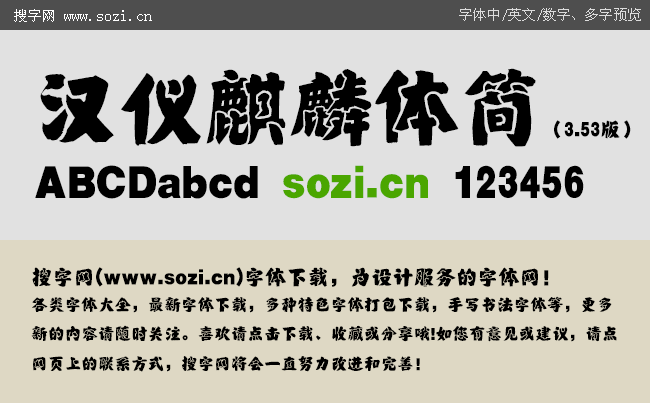
漢儀麒麟體簡
搜字網(wǎng)提供一款漢儀麒麟體簡中文藝術(shù)字體下載,漢儀麒麟體結(jié)構(gòu)上吸取顏楷的端莊大氣、方正樸茂,又運(yùn)用疊筆勾白的表現(xiàn)手法突出筆畫間的層次關(guān)系。整體呈現(xiàn)出雄健渾厚卻又不失靈動(dòng)飄逸的效果,是傳統(tǒng)藝術(shù)融入現(xiàn)代思想的和諧之作?梢詰(yīng)用于廣告設(shè)計(jì)、平面設(shè)計(jì)、產(chǎn)品包裝、報(bào)刊雜志等領(lǐng)域。